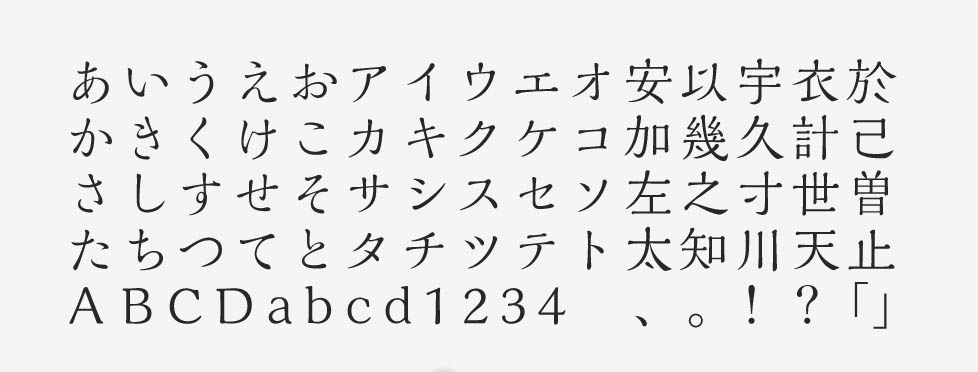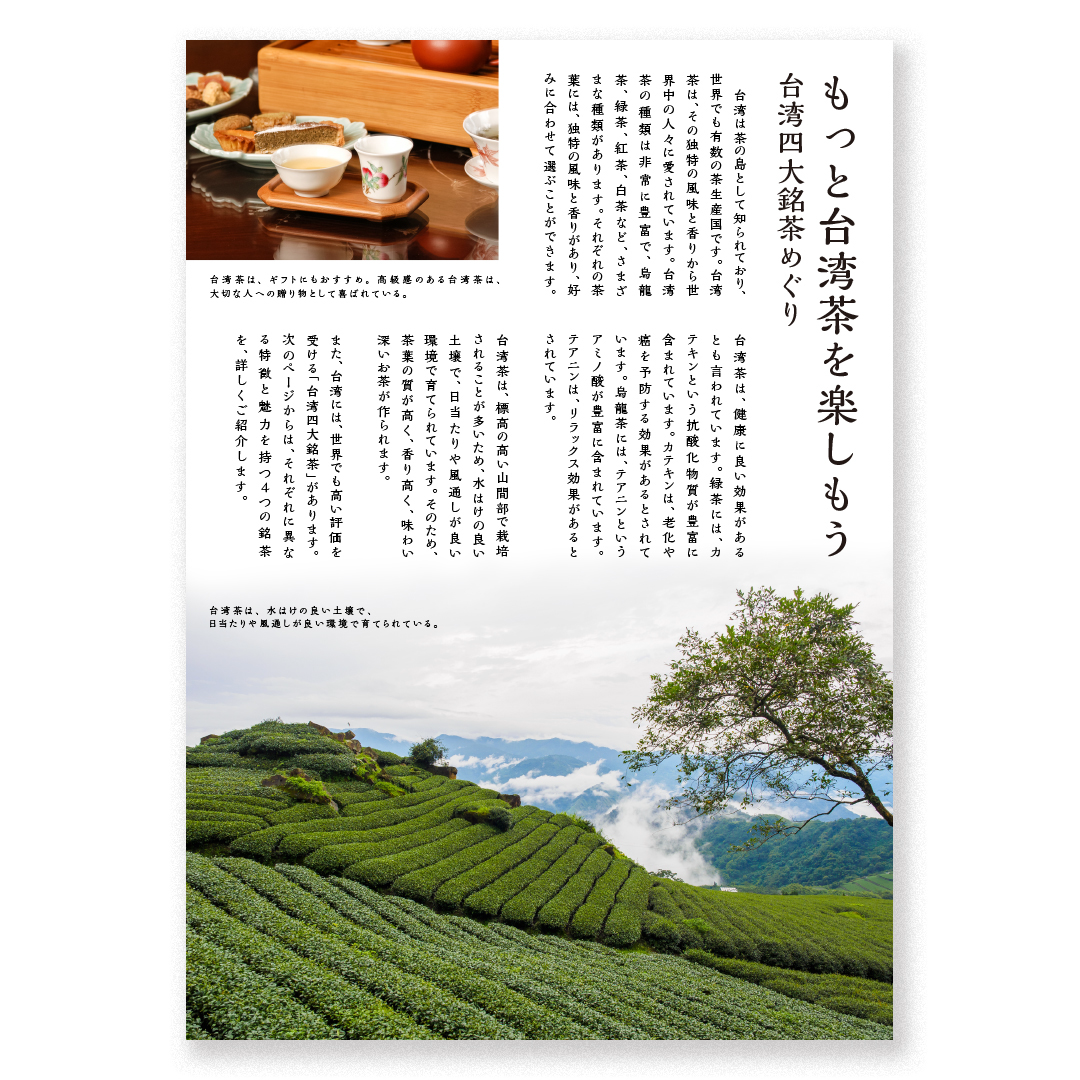
「解ミン 宙」について
「解ミン」は明朝体に隷書の筆法を取り入れた漢字を採用しているシリーズです。かな文字の違いによって「宙」と「月」があり、2013年に登場してから、さまざまな場面で活用されてきました。中国・台湾に関するイメージの箇所でも使われることが多いデザインフォントです。
「解ミン 宙」の特徴
明朝体の表情に隷書らしさを混ぜるため、右払いの部分が三角形状でうねるような「波磔(はたく)」のスタイルが取り入れられています。ウロコや画線には丸みがあり、レトロモダンで穏やかな印象です。オールドスタイルの明朝体では堅さが気になるときに、代替案として特に役立ちます。
かな文字は、抑揚を抑えた「月」とは大きく異なり、「宙」では活字時代の筆の運びが強く感じられます。ふくよかな肉付きで、優雅な佇まいを表現しやすいフォントです。
リリース以来ずっと愛用している書体で、このフォントにしかない声色(性格)がある名作フォントです。和モダンなイメージを出したい時にも、いつも有力な候補になっています。厚みのあるラインがやわらかく、遠方からの可読性が高いこともポイントです。